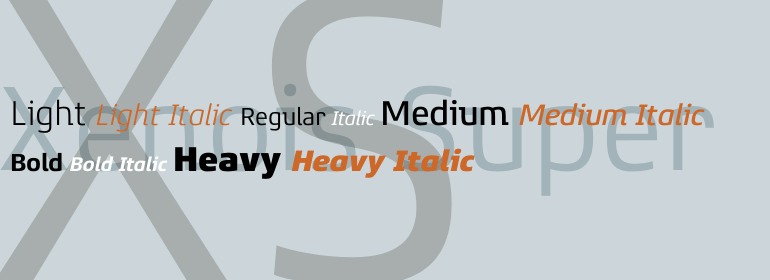
Xenois® Super
Xenois® Super,这款字体结构工整、笔画清晰,兼顾美观与易读性,适用于标题、正文、海报、包装、LOGO 等多种场景。字形优雅稳定,风格百搭耐看,适配日常排版与创意设计,让文字呈现更舒适、更具质感。Xenois® Super一笔一画,皆是细节,以均衡的比例、流畅的线条打造舒适视觉体验,字形端正大气,风格简约现代。无论是商业设计、品牌宣传还是日常排版,都能轻松驾驭,让文字更有格调与力量。Xenois® Super字体下载。
字体品牌: Linotype(Monotype) 设计师:Faulhaber,Erik 字体分类:衬线体 字体属性:外文 字符集:Unicode 发布时间: 2018